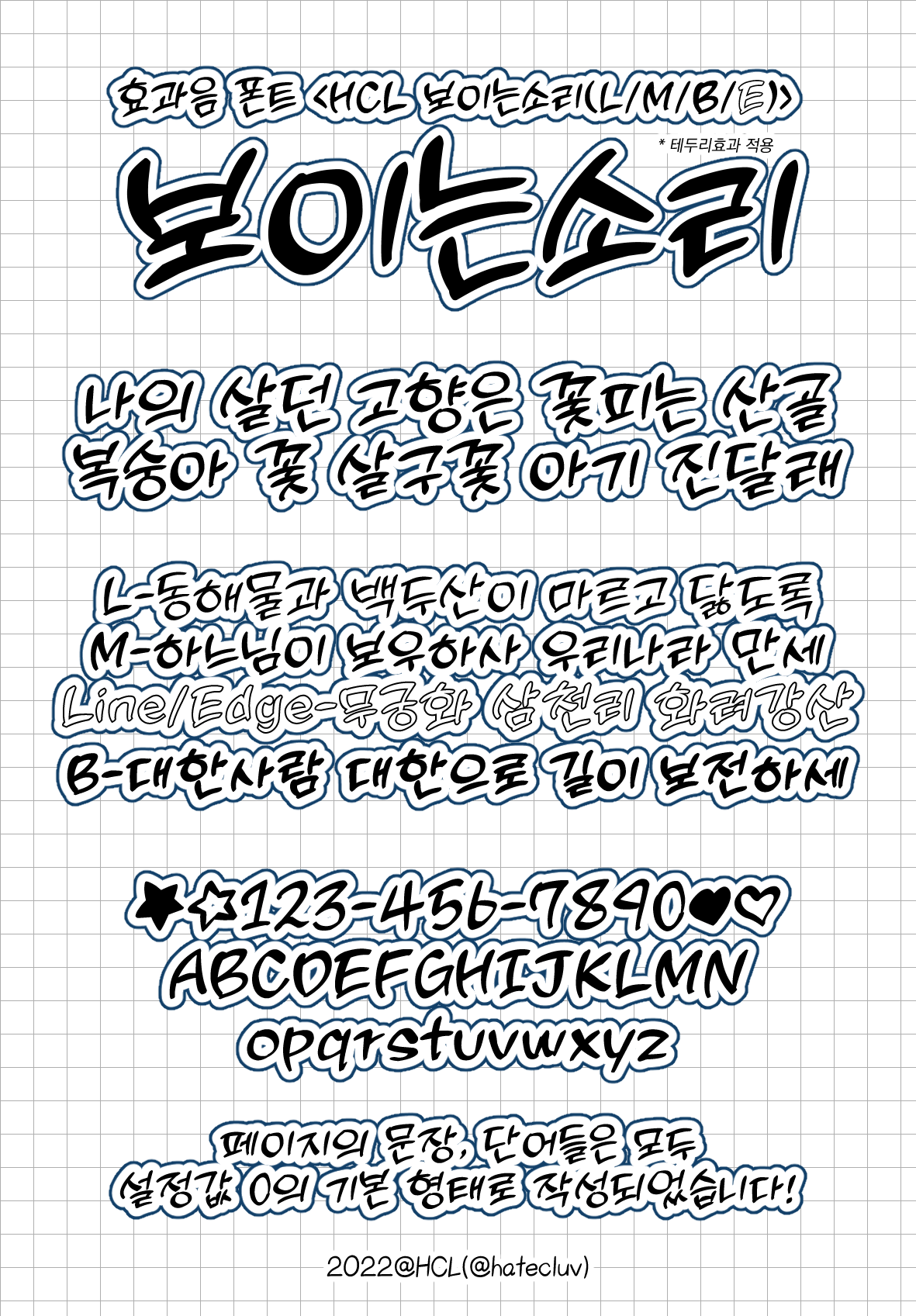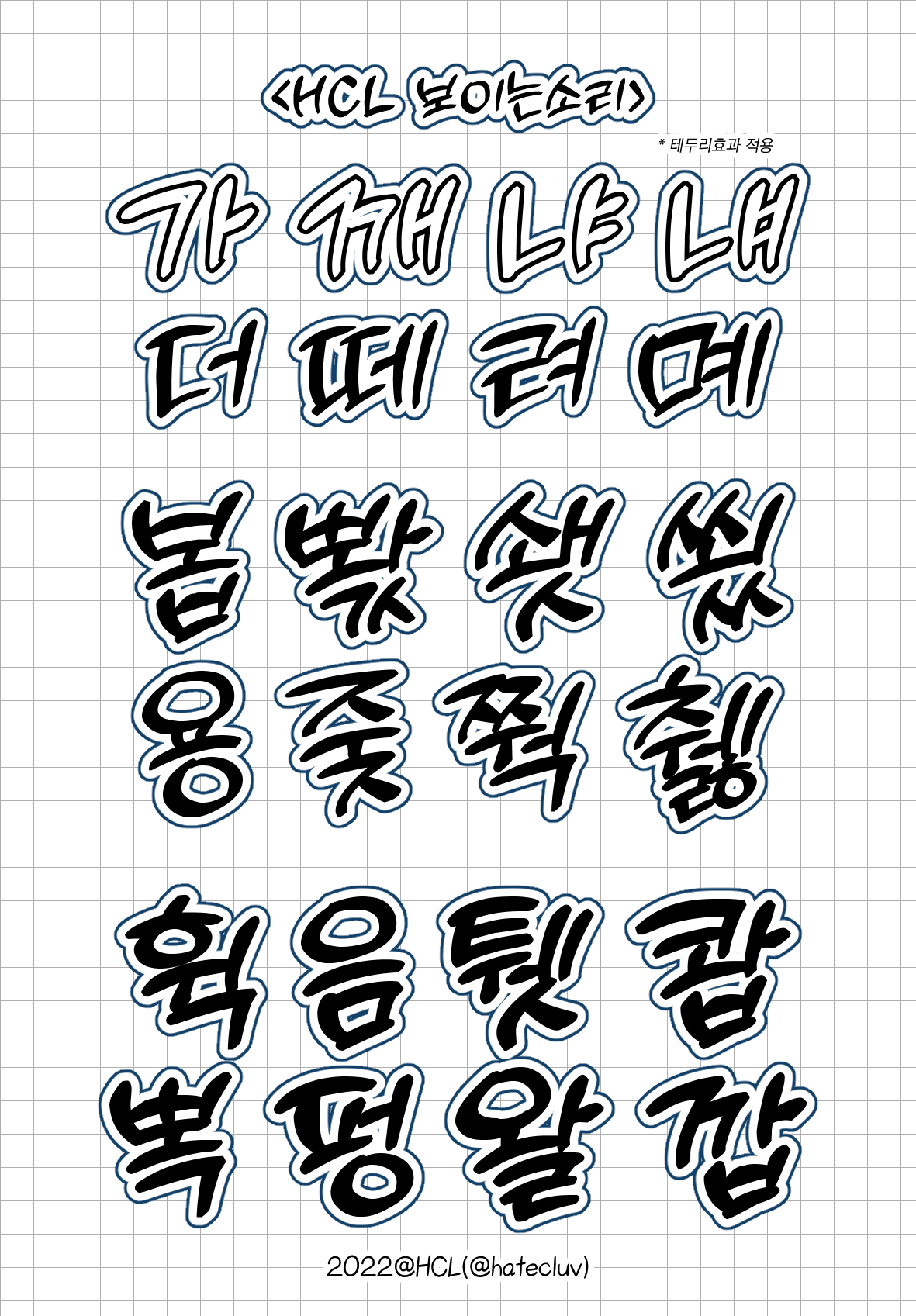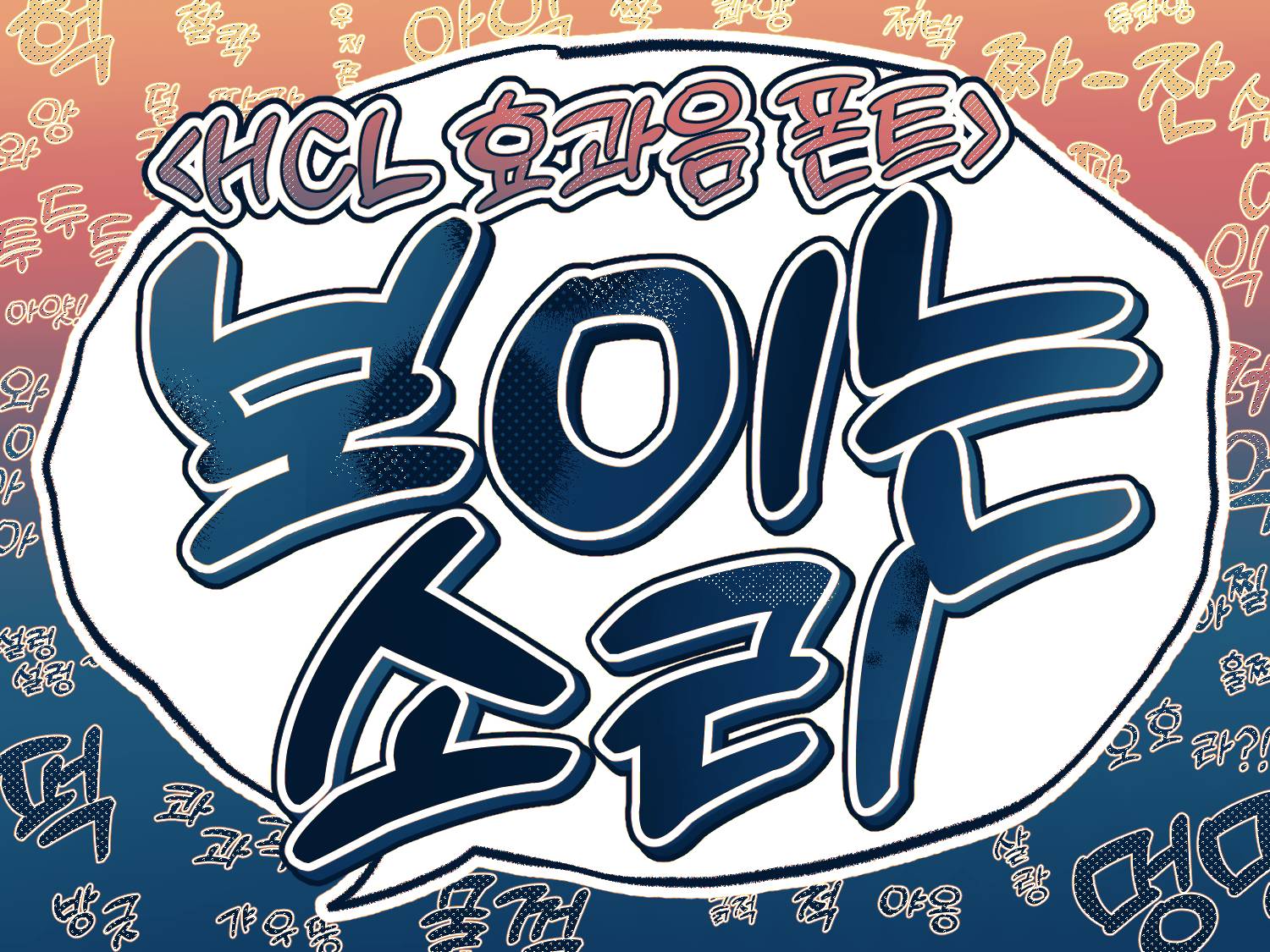
만화 효과음 느낌의 캘리그라피 폰트 <HCL 보이는소리> 입니다.
한글 조합 11172자 전체, 한글 기본 자모음(ㄱ,ㄴ,ㄷ,ㅏ,ㅑ,ㅓ...) 52자와 영문 대소문자, 숫자, 키보드 쉬프트 특수문자, ☆★♡♥, ©(카피라이트 문자) 등 한글 외 120글자를 지원합니다.
HCL 보이는소리